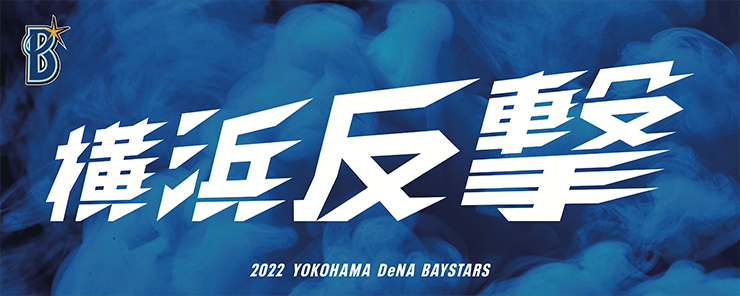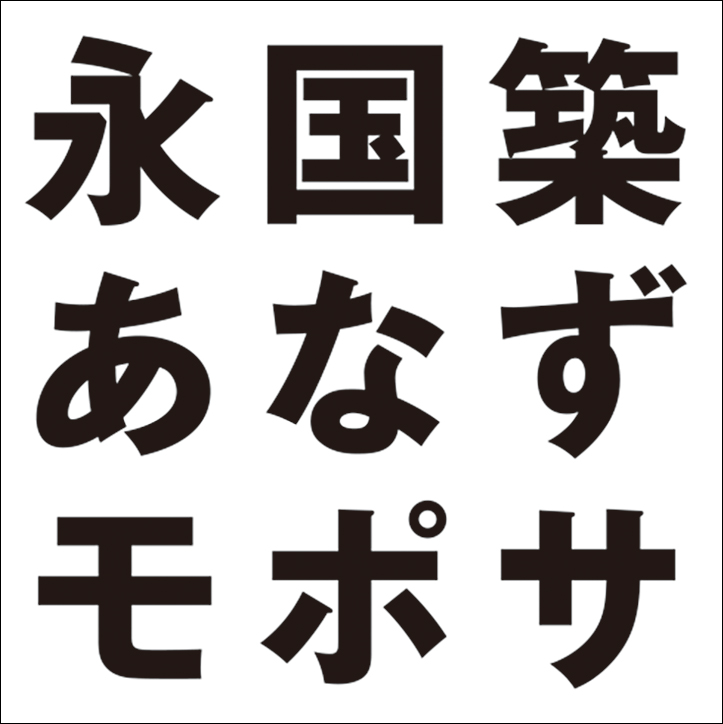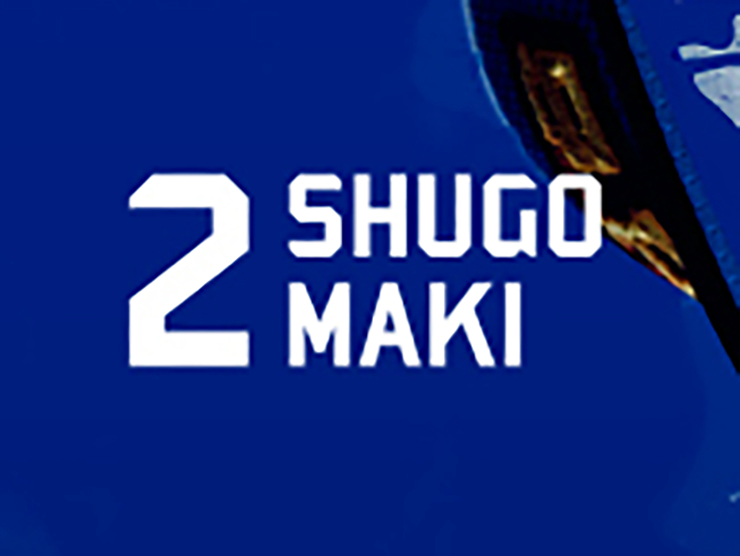
今回は、プロ野球球団「横浜DeNAベイスターズ」の広告ビジュアルの使用フォントについて、デザインを手がけた榮良太[博報堂]さんに取材。エッジの効いたインパクトのあるキャッチコピーの文字やデザインコンセプトなどを紹介します。
【広告ビジュアル『横浜DeNAベイスターズ』のデザインコンセプト】
勢いを感じさせる文字で選手の情熱や意志の強さを表現
プロ野球・横浜DeNAベイスターズの2023年開幕シーズンビジュアルおよびシーズンを通して掲載されるメッセージビジュアル。メッセージビジュアルはベイスターズの監督・選手紹介を兼ねたもので、全部で24種類用意されている。本記事では、そのうち牧秀悟選手のビジュアルをピックアップして紹介する。いずれのビジュアルも、チームの優勝に賭ける情熱と強い想いが、監督および選手たちの写真や飛び散ったインクの飛沫、筆のかすれ、勢いを感じさせるタイポグラフィなどで表現されている。
アートディレクターの榮良太さんによれば「2023年のビジュアルのテーマは『勝利の血潮』。絶対に優勝するぞ! という選手の想いや覚悟、情熱が身体の中から滲み出て吹き出しているイメージで制作しました。メッセージビジュアルでは、選手の動きにリンクするよう至るところに飛沫=血潮をあしらって、その意志の強さを表現しています。開幕シーズンビジュアルでは、堂々と立っている選手たちの背景に『V』の字を大きく配置して『優勝』への強い決意をイメージさせました」とのことだ。
広告ビジュアル『横浜DeNAベイスターズ』の使用フォント01:「オリジナル」
筆で書いたような右肩上がりの文字で勢いを
キャッチコピー「横浜開幕」やメッセージ「俺を頼れ。俺に任せろ。」、シーズンスローガン「横浜頂戦」部分は、ビジュアルのテーマに合わせて作り起こされたオリジナルの文字。筆で書いたような右肩上がりのデザインで、チームの“勢い”や優勝に賭ける強い“想い”が表現されている。上図と上中図は、今年のシーズンスローガン「横浜頂戦」の文字と昨年のシーズンスローガン「横浜反撃」の文字の比較。下図は、メッセージ部分。
榮さんによれば「昨シーズンは『2021年の最下位から這い上がってやる!』という気持ちを込めて右肩上がりの尖った勢いのある文字を制作しました。惜しくも2位で終わりましたが、『今年こそ必ず優勝してみせる!』という気持ちで今回の書体を作っています。昨年の文字の印象を継承しつつも、さらに勢いを感じさせるように、キービジュアルで使用している書道の筆のかすれのニュアンスを取り入れて“昨年の進化バージョン”を目指しました」とのことだ。
広告ビジュアル『横浜DeNAベイスターズ』の使用フォント02:「ゴシックMB101 B」
太めの風格あるゴシック体で堂々とした印象に
リードコピー「頂への戦いをはじめようか。」部分の文字は、骨太で風格あるゴシック体「ゴシックMB101」(モリサワ)に。監督や選手たちの強い想いを表現するため、ウェイトは太めの「B」が選択された。榮さんによれば「『絶対に優勝するぞ!』という強い意志を込めたかったので、太めのゴシック体で堂々とした力強いイメージにしました」とのことだ。
広告ビジュアル『横浜DeNAベイスターズ』の使用フォント03:「Bombardier Regular」
直線的で知的な欧文書体を選択
チーム名や選手名の欧文部分は、カクカクした直線的なフォルムが印象的な「Bombardier Regular」(Apostrophic Labs)がベースに。あえて他の要素とは異なるイメージの書体を使うことで全体のデザインにメリハリがつけられている。榮さんによれば「背景の書のエネルギッシュかつ情熱的で有機的な形に対して、冷静で知的なイメージの直線的な書体を選ぶことで、画面の中に緩急をつけました」とのこと。